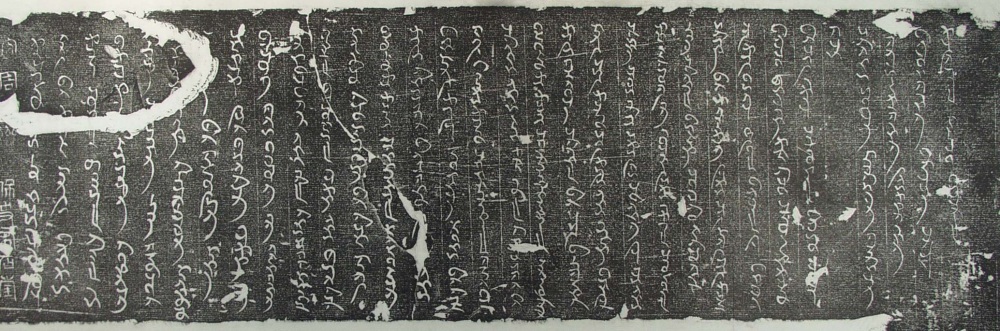
ソグド文字>大周凉州薩保史君墓誌拓本
| 資料名 | 大周凉州薩保史君墓誌拓本 |
| 文字/言語 | ソグド文字・漢字/ソグド語・漢語 |
| 行数 | ソグド文32行。漢文18行 |
| 大きさ | 縦20cm、横86cm |
陝西省西安市出土ソグド人墓の墓誌拓本。
右はソグド文字ソグド語、左は漢字漢語。漢文1行目に篆書体で「大周凉州薩保史君石堂」とある。
妻とともに北周大象二年(580)に合葬されたこと等が記されている。